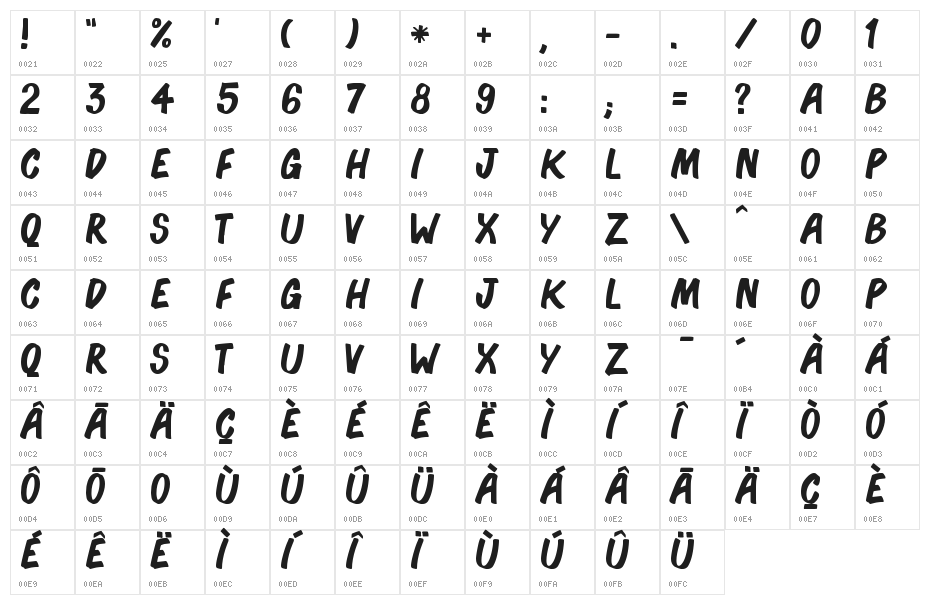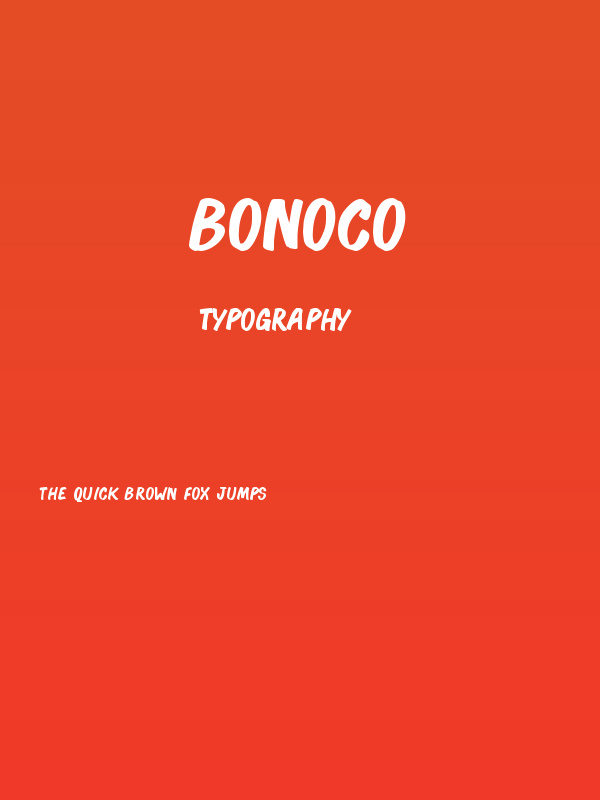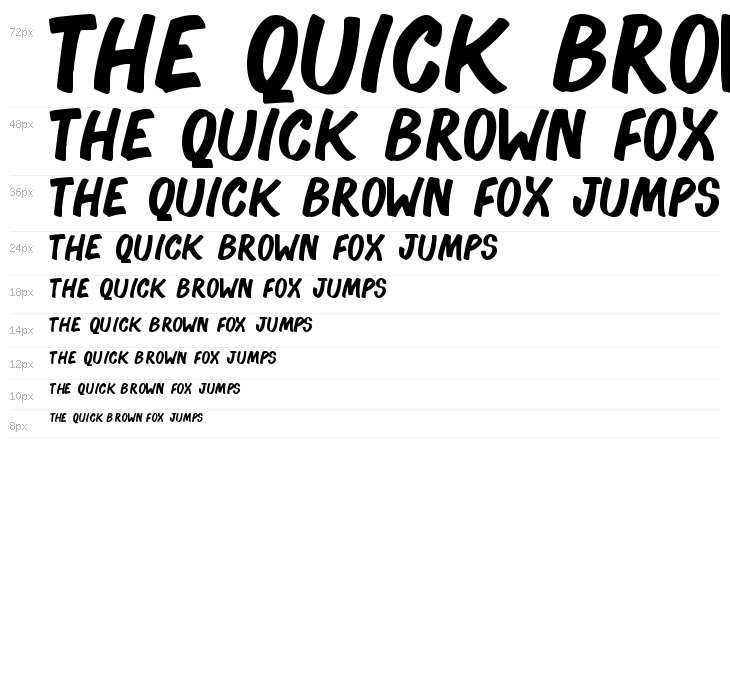
Bonoco Font
| Gesamtstil | Playful, Energetic |
| Vorgeschlagene Projekte | Great for children's books, playful branding, casual invitations, and social media graphics. |